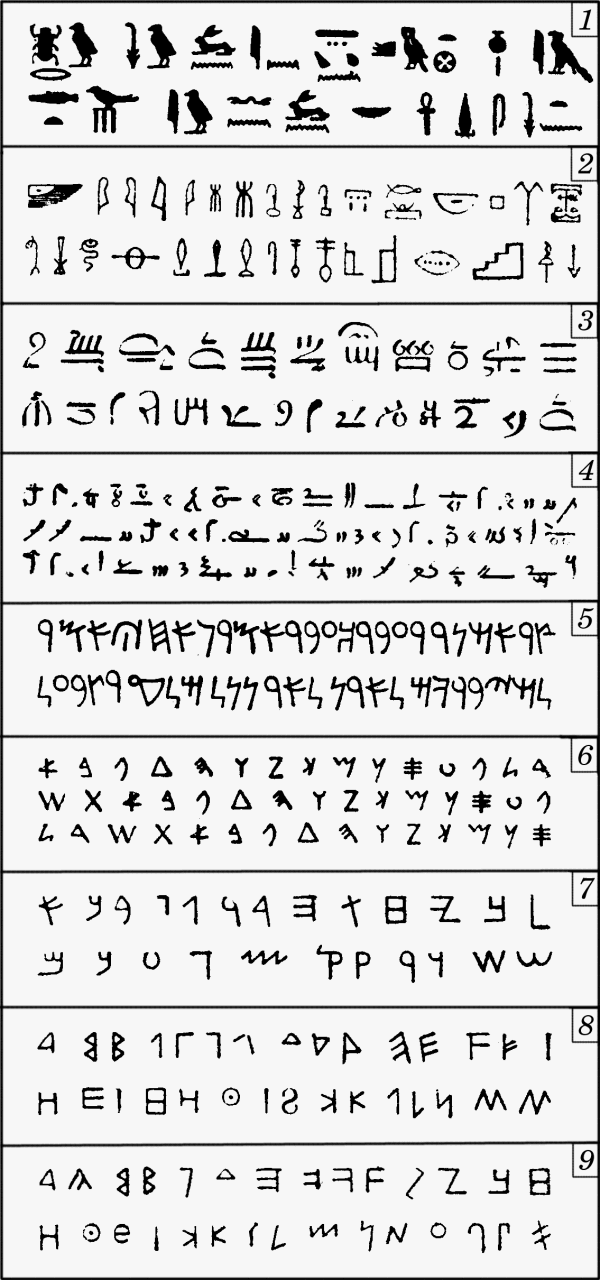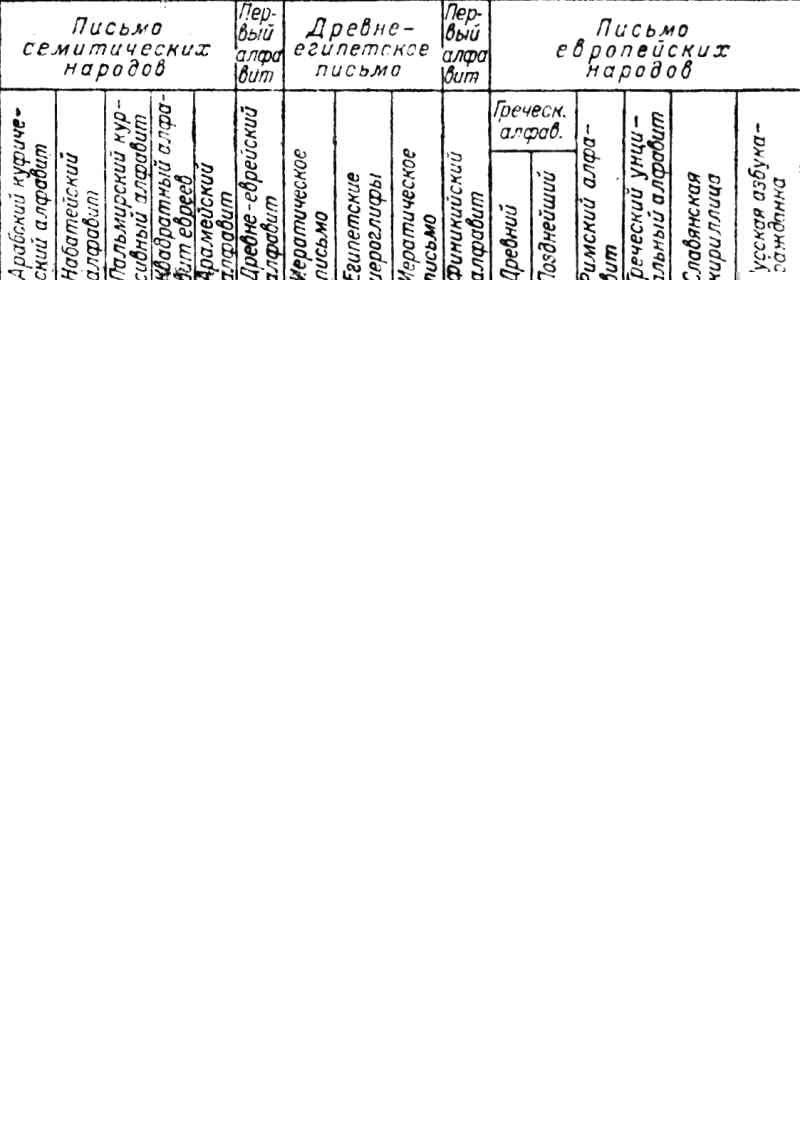
1. Развитие шрифта
Возникновение письменности
Древнейший язык человечества — язык жестов.
"Человечество начало свое общение линейной, или ручной, речью. языком жестов и мимики. Оно продолжило его звуковой речью, языком членораздельных звуков...
...Линейный язык вполне отвечал и качеству и уровню умственного развития человечества начальных эпох и технически и идеологически. Человечество тогда мыслило дологическим мышлением, без отвлеченных понятий, представлениями в образах".
Звуковой язык возник тогда, когда человек уже был на высокой ступени умственного развития. Этот язык не начался с отдельных звуков, слагавшихся в слова. Отдельные членораздельные звуки появились позже. Вначале язык состоял из комплексных звуков.
Рис. 284 Символические знаки в картинном письме американских индейцев: Слева направо: "Жизнь" (рогатая змея); "Смерть" (изображение животного вверх ногами); "Любовь" (два соединенных сердца); "Проворный, ловкий" (Человек с крыльямми вместо рук); "Война" (Натянытуй лук); "Мир" (трубка украшенная перьями); "Внимание, слух" (голова с зигзагообразными линиями от ушей) |
"С развитием звуковой речи, естественно, возросло значение не только цельных звуковых комплексов, многочисленных слов,... но и каждого звука. С развитием звуковой речи каждый звук получил самостоятельное бытие в общественном сознании, в сознании человечества. Раньше, до возникновения я развития звуковой речи, представления о самостоятельном восприятии отдельных членораздельных звуков не было и не могло быть. Звуковая речь начинается не с выработки отдельных звуков, а с использования отдельных цельных комплексных звуков, впоследствии развившихся в звуковые комплексы из трех фонем, четырех элементов, сначала доводивших свою членораздельность лишь до нераздельного произношения трехзвучности согласного, согласного = SAL, BER, JON, ROШ, тогда не имевших каждый той составности из трех звуков, которую мы наблюдаем теперь. ...Работе над осознанием звуков как самостоятельных величин предшествует работа над отличением гласного от согласного, усилением гласного и согласного путем удлинения (долгота гласных, так наз. удвоение согласных) и ударения, resp. повышения голоса, повторения целого звукового комплекса, т. е. путем явлений музыкального порядка, получивших свое выражение, как это выясняется, в процессе развития пения и музыки, независимо от звуковой речи, до ее возникновения".
Эти явления музыкального порядка, как пишет акад. Марр, возникли в коллективном трудовом процессе. Сложный путь развития прошла и письменность. Примитивная форма письма — рисуночное письмо (пиктография). Она существовала еще у доисторического человека. Пиктография представляет собой комбинацию рисунков, передающих сочетание простейших смыслов, независимо от их звучания.
Пиктограмма могла передавать лишь понятия, достаточные для низкой ступени развития человечества, например реальные предметы или простейшие явления. По мере развития культуры зрительный знак развивался в двух направлениях: в сторону создания условного начертания и в сторону создания символического выражения для отвлеченных понятий и сложных явлений. Из пиктограммы, приобретающей условное начертание, принимающей символическое значение, рождается идеографическое письмо (рис. 284).
Среди древнейших систем идеографического письма можно отметить египетские иероглифы, а также китайское письмо.
"Некоторые факты из истории отдельных идеографических систем письма (в частности, китайского) позволяют установить важное влияние на развитие пиктограммы в идеограмму так называемого "языка жестов", применяемого у многих первобытных народов для межплеменного общения. Поскольку жест, т. е. зрительный знак не графический, приобретает в этой форме общения отвлеченное значение, становится сигналом отвлеченного понятия, ясно, что здесь намечается путь для отыскания графических знаков для выражения отвлеченных значений. Графическое изображение символического жеста становится графическим изображением отвлеченного понятия, им выражаемого."
Таким образом, наличие у человечества условных зрительных знаков. одного типа (жестов) способствовало развитию простейших зрительных знаков другого типа (графических) в условные и отвлеченные начертания.
Крупнее: 600x1280, 67kb Рис. 285 Таблица шрифтов: 1 - иероглифы египтян, как они изображались на памятниках (около 3000 л. до н.э.); 2 - иероглифы из свитков (около 3000 л. до н.э.); 3 - иератичекий шрифт, образовался из 1 и 2, применялся только при письме на папирусе (около 3000 л. до н.э.); 4 - демотический шрифт, образовался из 3, применялся для коротких записей (около 700 л. до н.э.); 5 - финикийский шрифт. возник в середине 2-го тысячелетия до н.э., предположительно — корень всех европейских шрифтов; 6 - моабитский шрифт, вместе с 5 являеться корнем европейских шрифтов; 7 - древнееврейский алфавит, образовался из 5 и 6 или же появился одновременно с ними; 8 - древнегреческий шрифт, образовался из 5 и 6 около конца 2-го тысячелетия до н.э.; 9 - древнеитальянский шрифт, возник из 5 и 6, возможно из 8 |
В египетских иероглифах (рис. 285, 1) видимые предметы обозначались соответствующими изображениями (кисть руки, кружка, рот, палец и т. д.) или символическими знаками (солнце, луна, царь и т. д.). Для глаголов же употреблялись изображения близких слов, например две ноги — ходить, скипетр — властвовать, покидающая раковину улитка — выходить и т. д.
В иероглифах один и тот же знак мог обозначать различные понятия, так как при письме учитывались только согласные буквы, гласные же буквы опускались.
Поэтому изображение пальца teb—tb служило также для того, чтобы написать taibe (сосуд), tba (10000). Изображение рта (hro) обозначало также глагол я отдыхать" (here) и т. д.
Многие знаки, таким образом, с течением времени утеряли свое идеографическое значение и стали служить для передачи определенных слогов. Так возникло слоговое (силлабическое) письмо.
При дальнейшем развитии слоговое письмо постепенно превратилось в звуковое (фонетическое), в котором каждый знак обозначал определенный звук.
Так, например, изображение цепи (ht) стало знаком для буквы h, изображение змеи (zt) — для буквы z и т. д. При этом один и тот же звук можно было обозначать различными рисунками, лишь бы только их названия начинались одной и той же буквой.
Новая газетная гарнитура значительно превосходит по удобочитаемости обычно употребляемые в настоящее время для набора газет шрифты типа обыкновенного (1, 2 и 6 гарнитуры). При создании новых гарнитур должен быть изучен огромный опыт Западной Европы и особенно Америки, накопившийся за последние 30 — 35 лет. Художнику-шрифтовику, задумавшему создание новой типографской гарнитуры, обязательно придется приобрести серьезную теоретическую подготовку, познакомиться со многими опытами и исследованиями, чтобы установить наилучшее начертание каждой буквы.
Рис. 342 Шрифт "бодони" Научноиследовательского института Огиза |